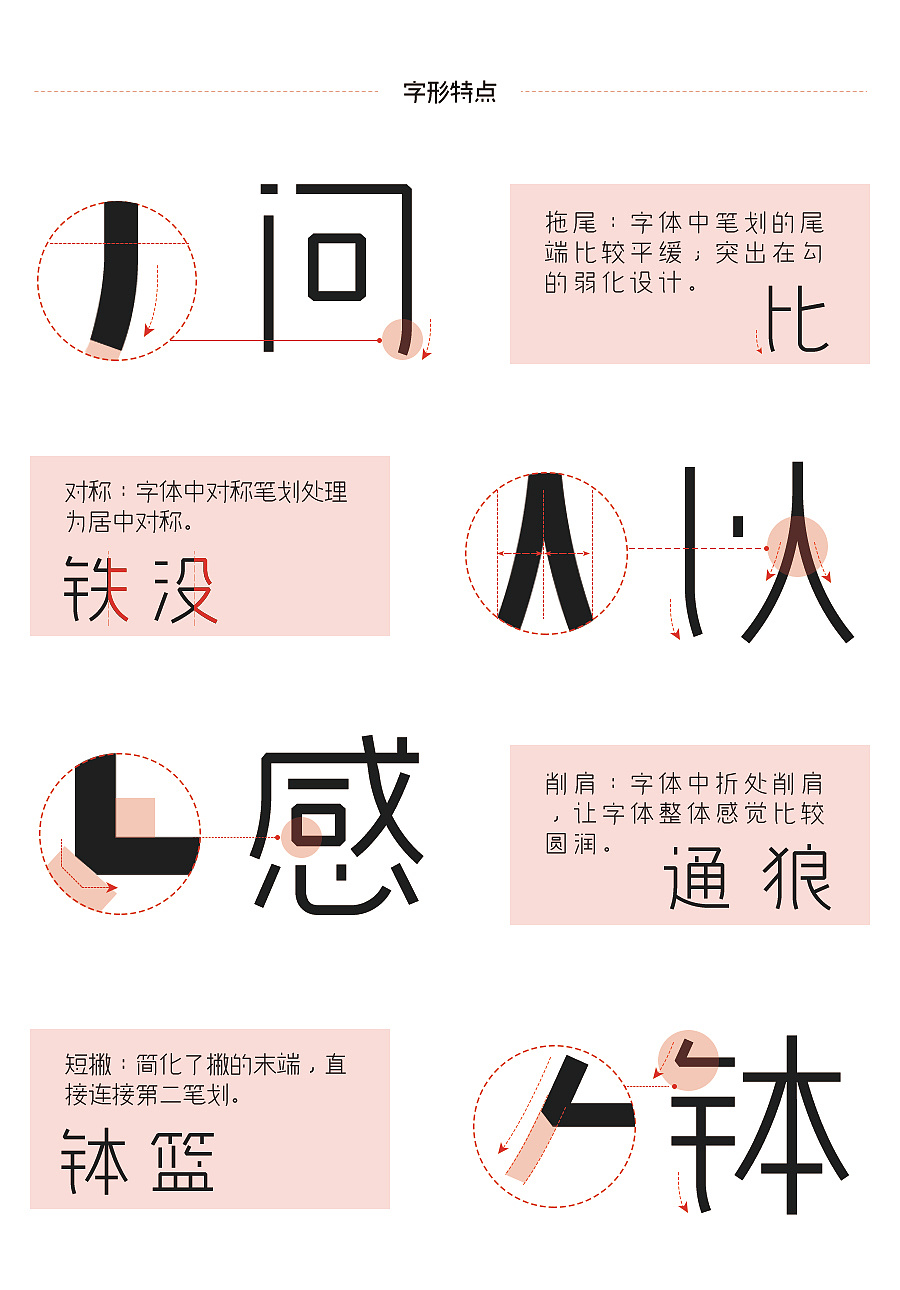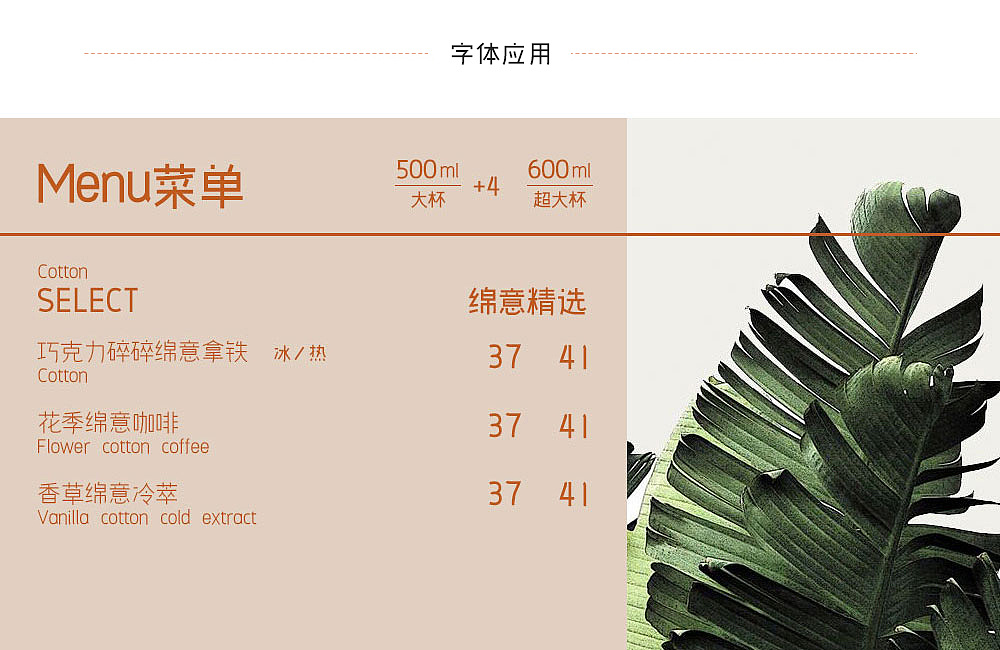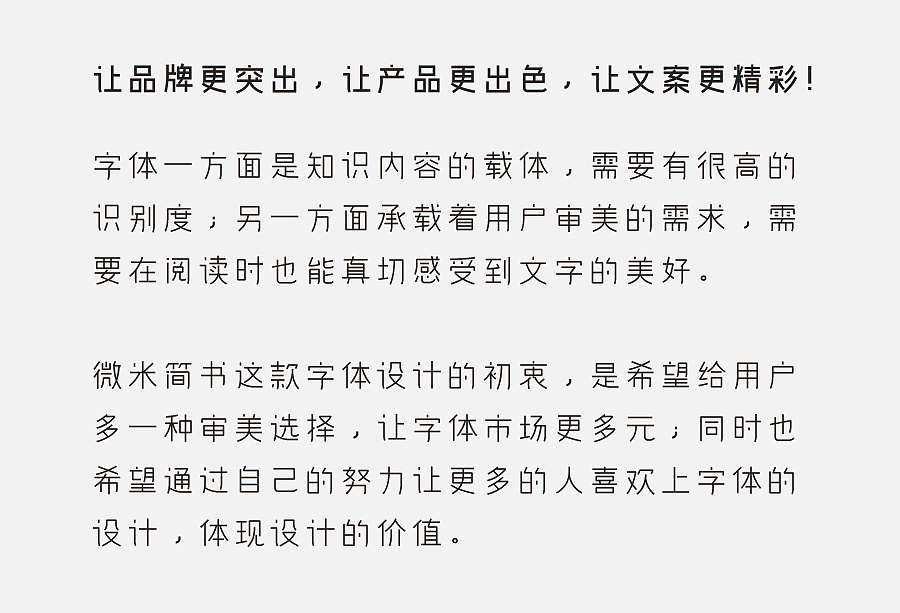
微米简书字体-让品牌更突出,让产品更出色,让文案更精彩!字体一方面是知识内容的载体,需要有很高的识别度;另一方面承载着用户审美的需求,需要在传递信息的同时,也能让用户真切感受到文字的美好。
「 微米简书 」这款字体设计的初衷,是希望给用户多一种审美选择,让字体风格更多元化;同时也希望通过自己的努力让更多的人喜欢上字体设计,体现字体设计的价值。